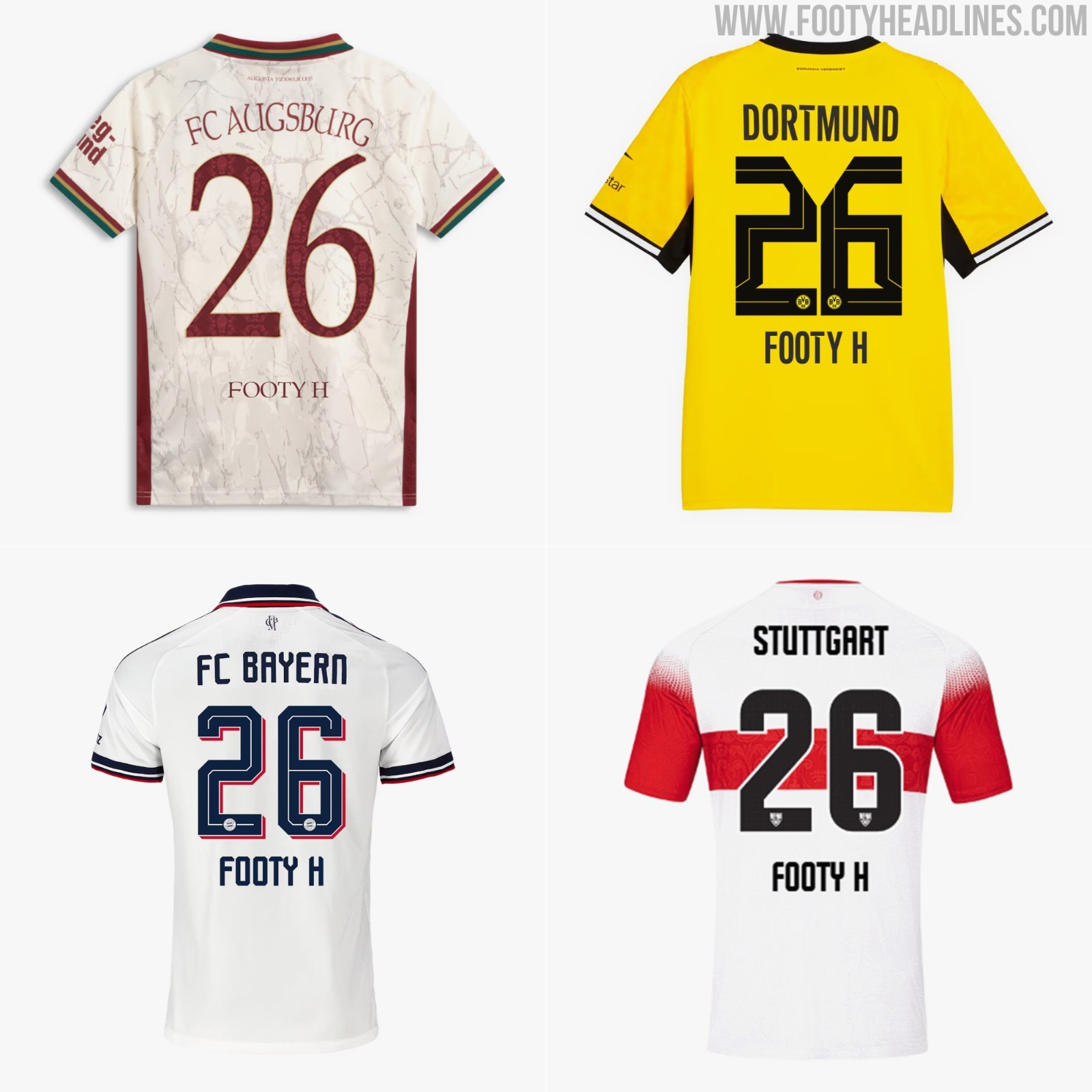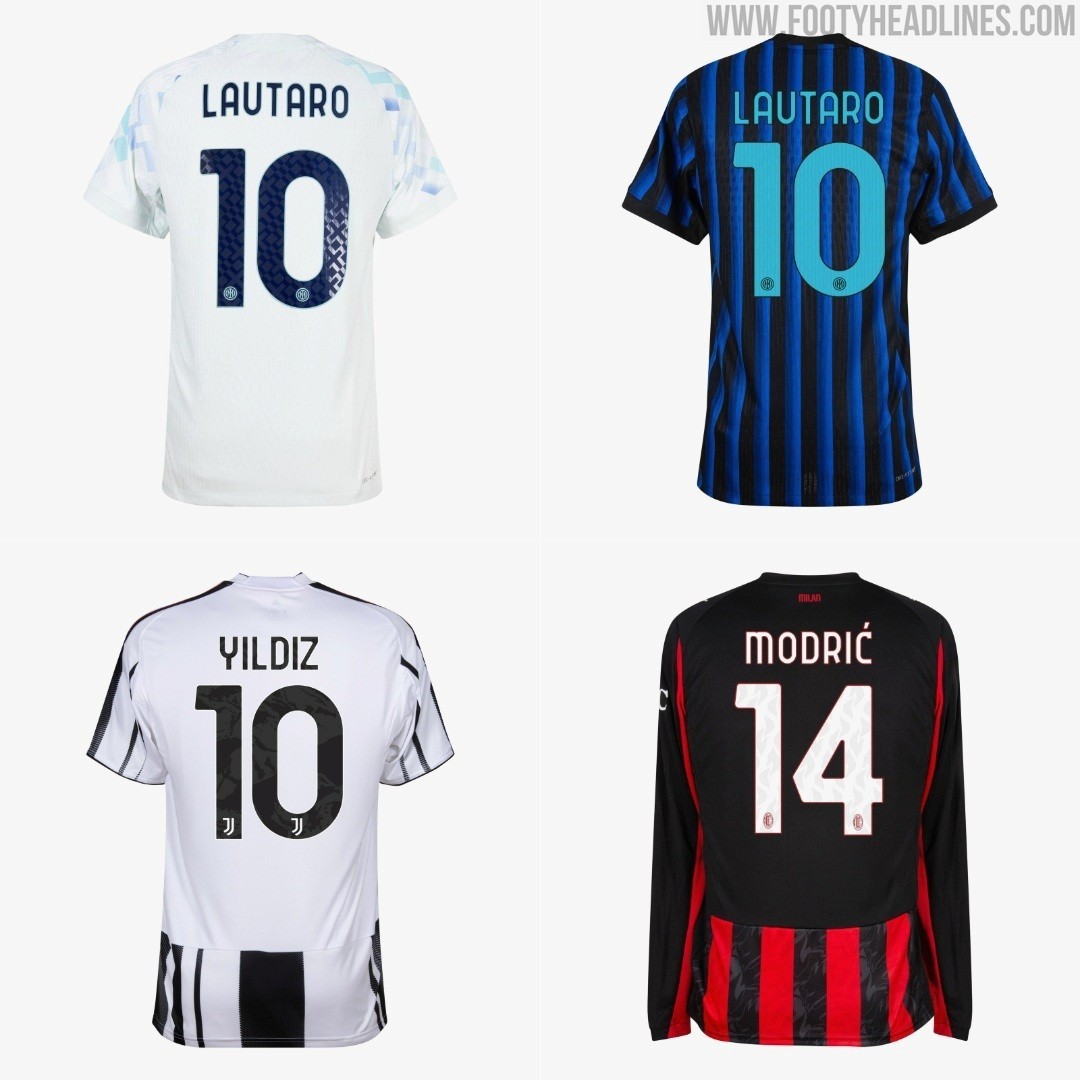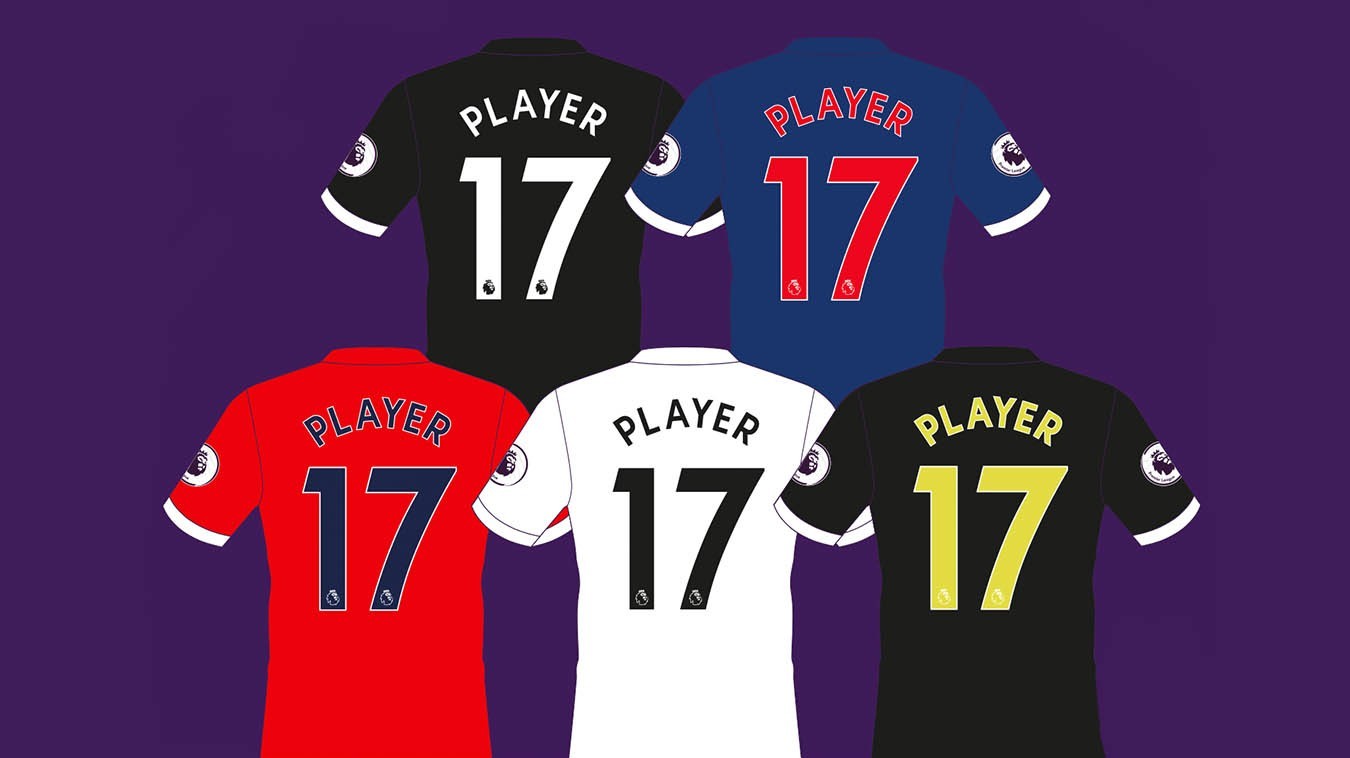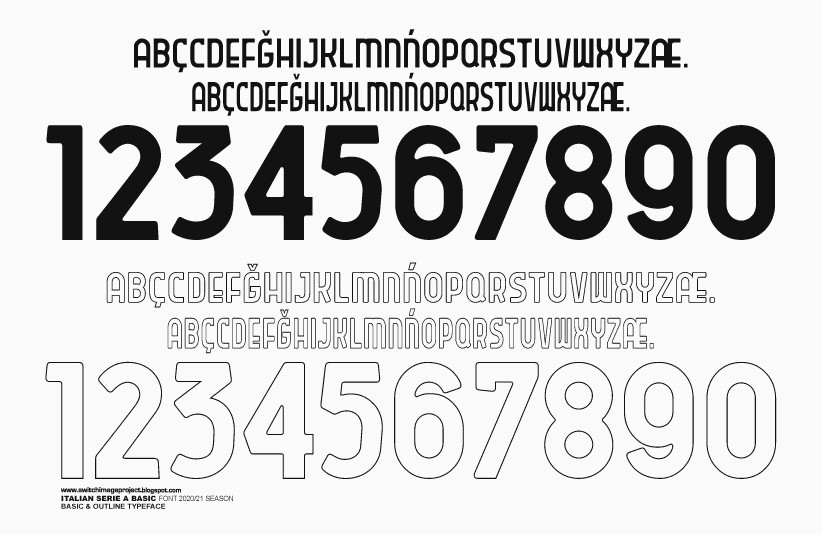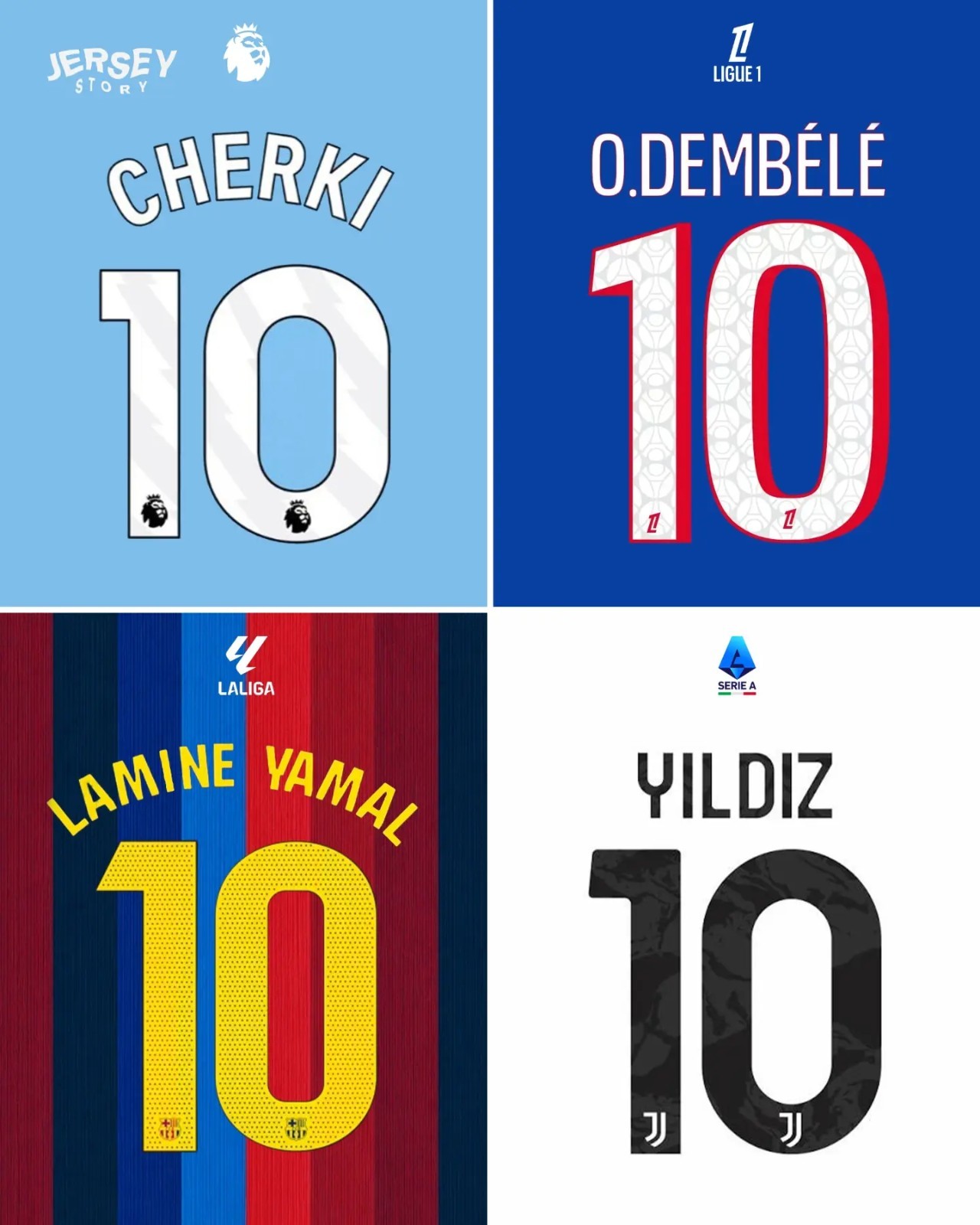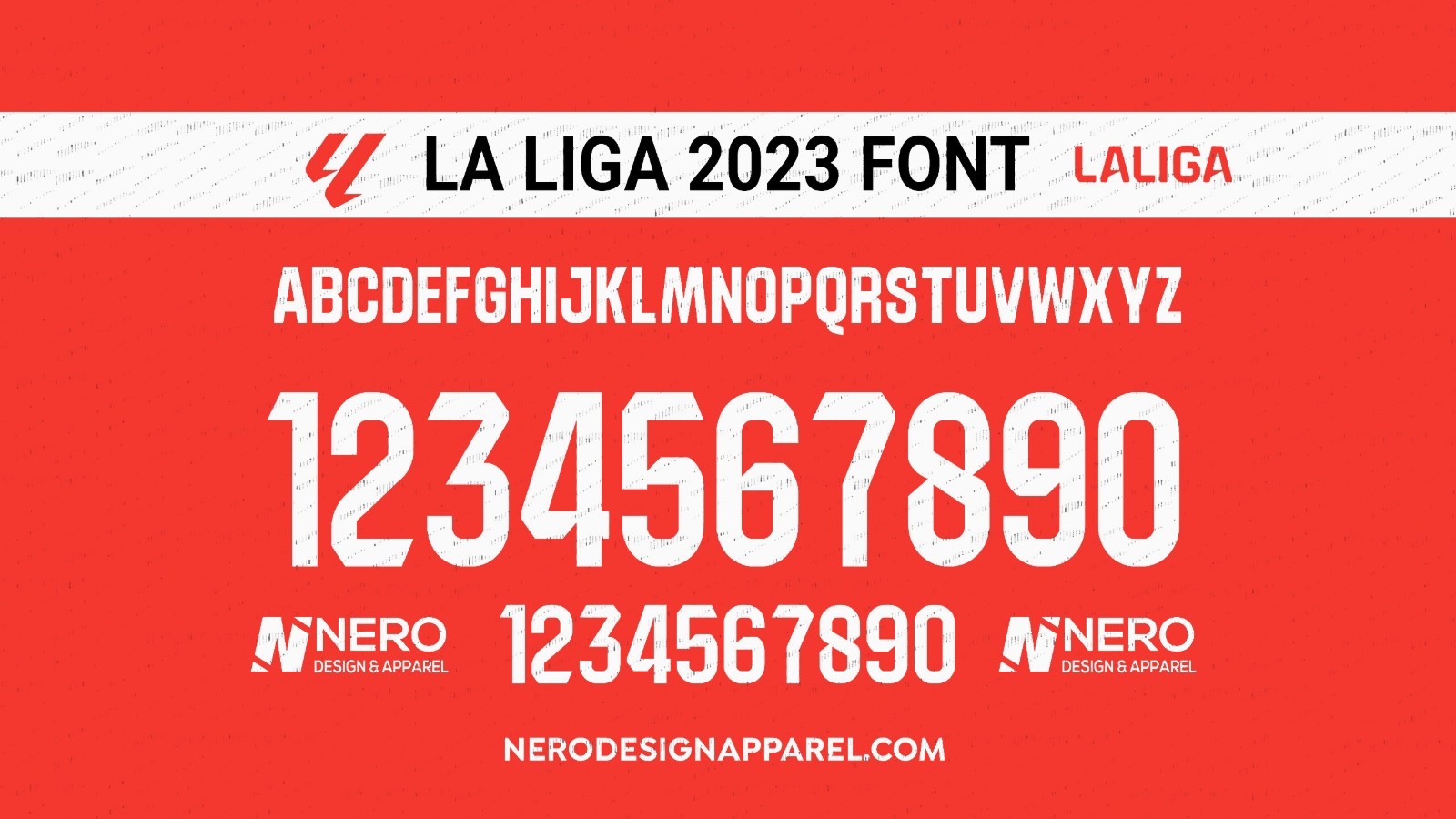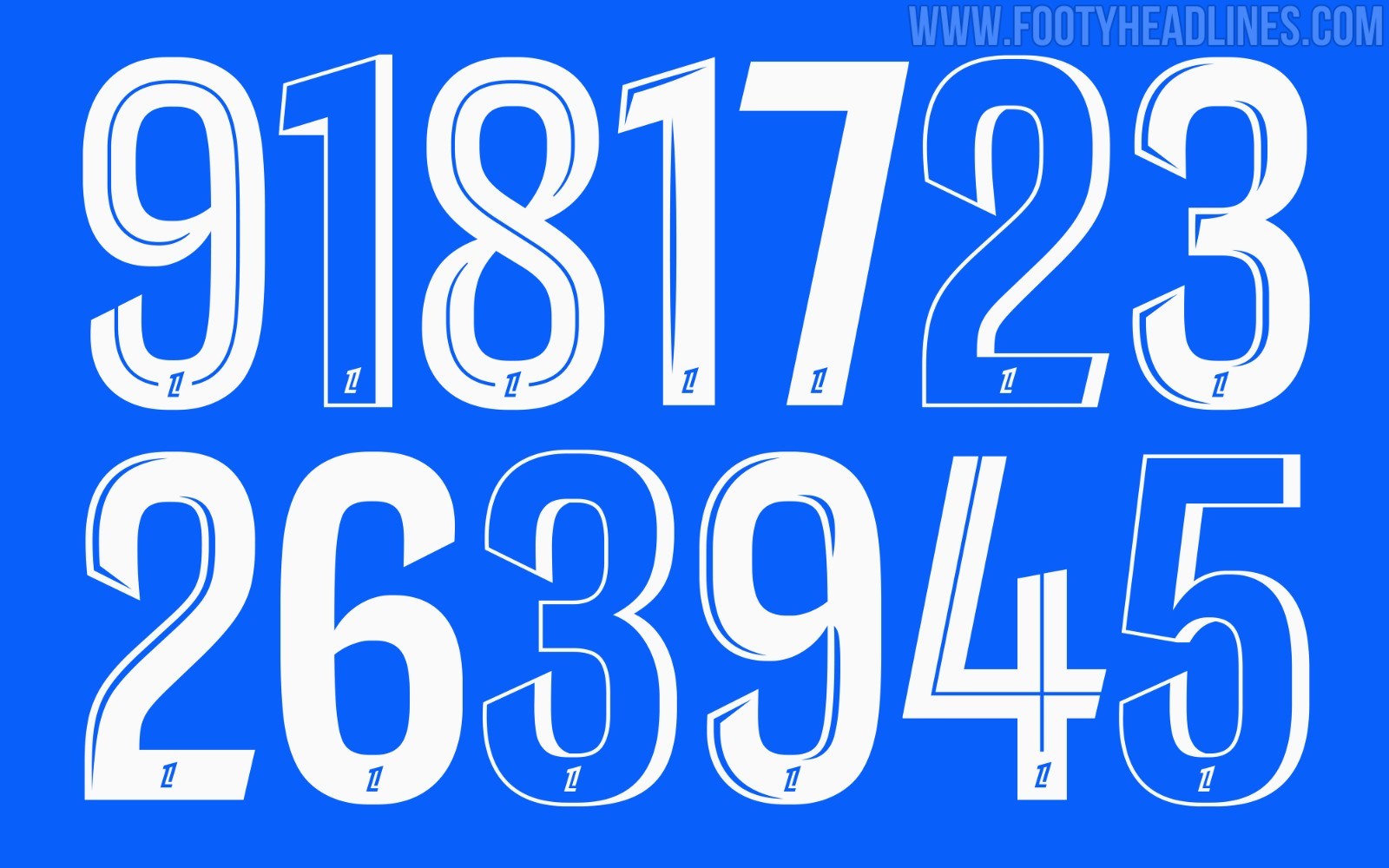
Vergleich der Schriftart-Richtlinien für Trikots: Die Bundesliga ist die einzige Top-Liga, die maßgeschneiderte Schriftarten zulässt
• Die Einzigartigkeit der Bundesliga: Im Gegensatz zu anderen europäischen Top-Ligen ist die Bundesliga die einzige, die ihren Vereinen völlige Freiheit bei der Gestaltung individueller Schriftarten für Namen und Nummern auf den Trikots gewährt.
• Das strengste System der Premier League: Die Premier League hat das restriktivste System unter den Top-Ligen, bei dem alle Vereine eine einzige offizielle Schriftart mit nur fünf zugelassenen Farboptionen verwenden müssen, was jegliche Individualität verhindert.
• Standardisierung mit variabler Flexibilität: La Liga, Serie A und Ligue 1 haben ebenfalls standardisierte Schriftart-Richtlinien, erlauben aber unterschiedliche Grade an Anpassung, wie individuelle Farben, Muster oder die Wahl aus mehreren Schriftarten und speziellen Designs für bestimmte Anlässe.
In den letzten zehn Jahren haben die meisten großen europäischen Ligen standardisierte Schriftart-Richtlinien für ihre heimischen Wettbewerbe vorgestellt, um die Lesbarkeit bei Übertragungen zu verbessern und eine einheitliche Markenidentität zu präsentieren, doch jede Liga geht bei der Festlegung der Namensschriften mit unterschiedlicher Strenge vor. Ein riesiges Dankeschön an unseren Partner Jersey Story für die Grafik und die Idee zu diesem Artikel.
Von strenger Einheitlichkeit zu individuellen Designs: Schriftarten auf den Trikots in Europas Top-5-Ligen
Vier der allgemein als Top-5-Ligen angesehenen Ligen haben einheitliche Schriftarten – wir werfen einen Blick auf die verschiedenen Schriftarten.
Premier League
Die Premier League hat das strengste System: Alle 20 Vereine müssen eine offizielle Schriftart mit nur fünf zugelassenen Farboptionen verwenden. Dieser Ansatz ist zwar sehr effizient, führt aber in manchen Fällen nicht nur zu Farbabweichungen, sondern verhindert auch jegliche Individualität.
La Liga
In der spanischen La Liga sind ebenfalls ligaweit einheitliche Vorlagen vorgeschrieben, allerdings dürfen die Vereine die Farben und die Details des Wappens am unteren Rand der Rückennummern individuell anpassen.
Serie A
In der Serie A gilt dasselbe wie in der La Liga, aber die Mannschaften können der Schriftart ein individuelles Muster hinzufügen, das oft von den Teams verwendet wird.
Die Rückennummern der Serie A 25/26 sind unglaublich detailreich im Trikot
Ligue 1
Die französische Ligue 1 geht in Sachen Flexibilität noch einen Schritt weiter und erlaubt den Teams, aus drei verschiedenen Schriftarten zu wählen. Zu besonderen Anlässen dürfen die Teams eine eigene, einzigartige Schriftart für ihre Trikots verwenden. PSG hat zum Beispiel bei „Le Classique“ verschiedene Schriftarten eingesetzt, darunter „Gothic“ in der Saison 2024/25, eine Schrift im Mandarin-Stil zum chinesischen Neujahrsfest und eine arabische Schrift für den Trophée des Champions.
Bundesliga
Im Gegensatz dazu ist die deutsche Bundesliga die einzige Liga unter den Top 5 ohne standardisierten Namenssatz. Die DFL gewährt den Vereinen völlige Freiheit bei der Gestaltung individueller Namen und Nummern, die auf jedes einzelne Trikotdesign zugeschnitten sind. So können Teams wie Bayern München, Borussia Dortmund und Bayer Leverkusen eine unverwechselbare Typografie entwickeln, was die Bundesliga zum letzten großen Hort für maßgeschneiderte Trikotbeschriftungen macht.